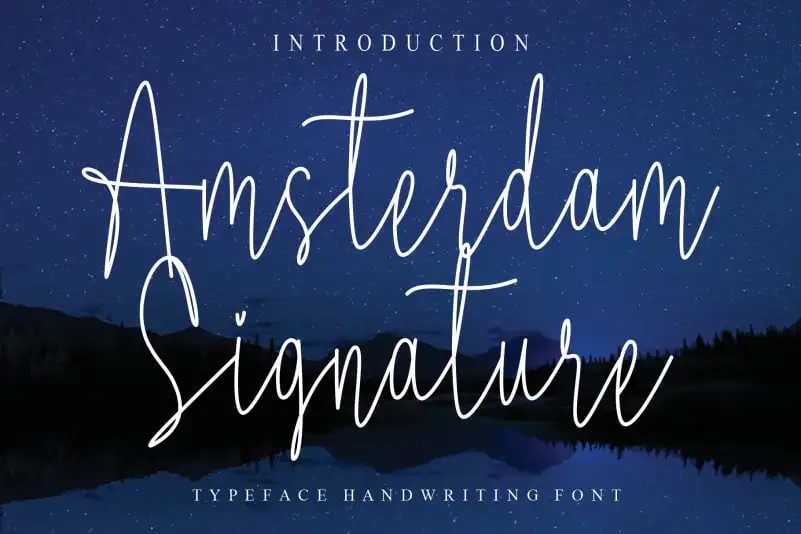
Descubra a sofisticação contemporânea da Amsterdam Signature Script Font com uma escrita manuscrita única e vibrante. Este estilo elegante é perfeito para criar textos memoráveis, seja em logotipos, cartazes ou design de websites. Com sua caligrafia minimalista mas impactosa, esta fonte oferece a opção de dar um toque especial a qualquer projeto gráfico. Especialmente criada para designers como você, nossa Amsterdam Signature Script Font é uma escolha perfeita que irá proporcionar-lhe uma experiência incomparável. A sua escrita suave e delicada combina com linhas finas e garridas com um toque de elegância, tornando-a perfeitamente adequada para qualquer projeto de design que você precise de uma mão criativa e inspiradora. Com a Amsterdam Signature Script Font, você não apenas recebe o benefício da estética única e inovadora, mas também experimenta um produto cuidadosamente projetado para maximizar sua versatilidade. Esta fonte é uma ótima opção para quem deseja adicionar um toque único e sofisticado a qualquer projeto gráfico que esteja envolvido.